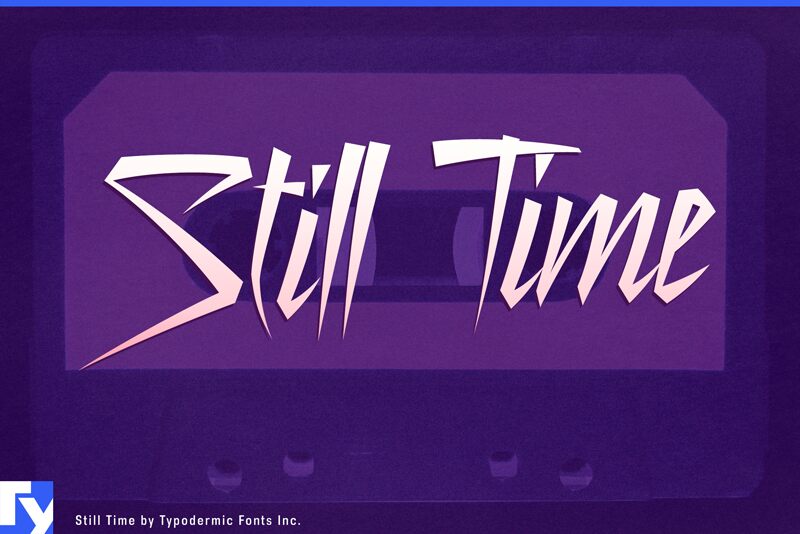
Still Time, zaprojektowany przez utalentowanego Raya Larabie, wyróżnia się rockandrollowym charakterem, emanując energią typową dla odręcznego pisma. Dzięki półlekkiej wadze, która jest przyjazna dla oka, a jednocześnie wystarczająco wyrazista, by przyciągnąć uwagę, Still Time zachwyca estetyczną płynnością i dynamiczną formą. Zadziorna osobowość tego kroju pisma czyni go doskonałym wyborem dla projektantów, którzy chcą dodać swoim pracom odrobinę buntu i stylu.
Ręcznie wykonana jakość Still Time nadaje mu autentycznego sznytu, idealnego do grafik związanych z muzyką, plakatów koncertowych, okładek płyt i wszelkich projektów, w których osobowość odgrywa kluczową rolę. Czytelność w połączeniu z surowym urokiem sprawia, że Twój przekaz nie tylko zostanie zauważony, ale poczuty z taką samą intensywnością, jak występ na żywo. Niezależnie od tego, czy chcesz uchwycić klimat indie, czy rockowe hymny, Still Time wzmocni wizualny efekt Twojego projektu dzięki swojemu unikalnemu, odręcznemu charakterowi.